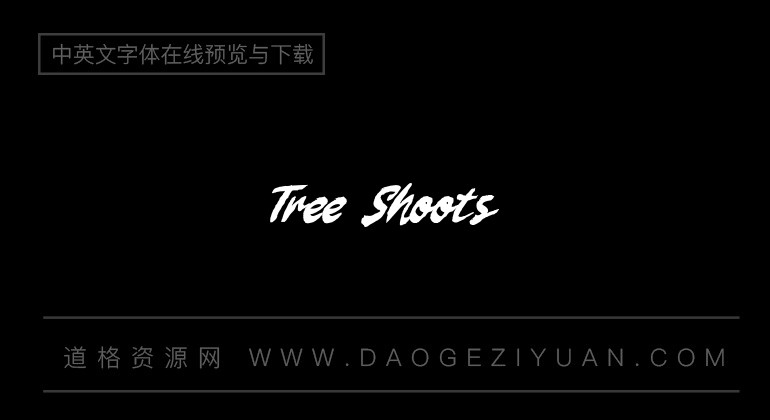
Tree Shoots 字体是一种手写风格的字体,具有非常自然和有机的外观。这个字体的特点是每个字母的末端都有一些类似于枝条或树枝的形状,这也是它得名的原因。 Tree Shoots 字体非常适合用于自然或有机主题的设计项目,如环保、农业、自然食品等。它也可以用于一些更加艺术性的项目,如画册、海报、插图等。这个字体非常易读,但同时也有一点奇特和独特的感觉,能够让你的设计作品脱颖而出。 Tree Shoots 字体有多种字重可供选择,包括正常、粗体和斜体,可以满足不同的设计需求。此外,它还有多种语言的字符集,可以支持多种不同语言的文字。内容介绍
Tree Shoots是一款非常不错的手写艺术字体,具有很好的视觉感,适合于文化类的宣传设计、商业类品牌的广告和产品包装设计以及个性化文字排版等较多场景。